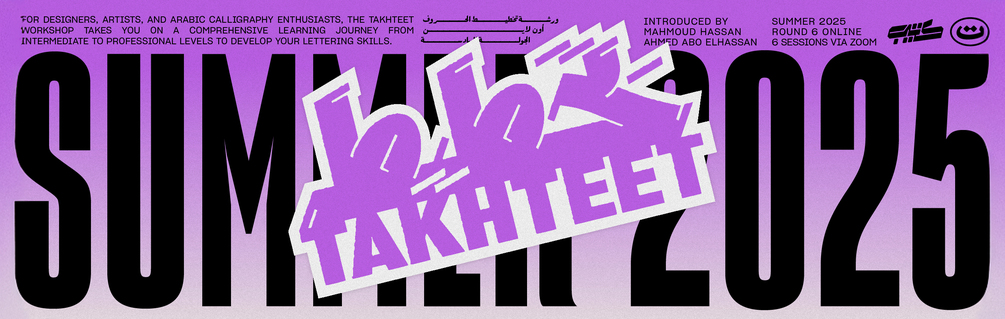
Takhteeet Arabic Lettering Online Workshop
نظرة عامة على الورشة:
ورشة "تخطيط الحروف" ورشة عمل عن بعد شاملة للمصممين والخطاطين لاحتراف تخطيط وتصميم الحروف العربية.
يقدمها أحمد أبوالحسن، مخطط حروف ومصمم هويات بصرية
ومحمود حسن، مصمم هويات بصرية ومخطط حروف ومدوّن في مجال التصميم.
* سيتعرف المشاركون على أساسيات الخط العربي ويتدربون على أنماط فنية مستوحاة من الخطوط الكلاسيكية والتصاميم الهندسية الحديثة.
* تغطي ورشة العمل العملية الكاملة لكتابة الكلمات بالخط، بدءًا من العثور على الإلهام وإجراء البحث إلى رسم المفاهيم الأولية، تنقيح التصاميم، ورقمنة العمل النهائي. من خلال التمارين العملية والإرشاد الشخصي من المدربين، سيطور المشاركون أساليبهم الخاصة في الخط ويكتسبون مهارات عملية في الطباعة وتكوين التخطيط.
* بحلول نهاية الورشة، سيكون لدى المشاركين أعمال خطية ومشروع نهائي يعكس رحلتهم الإبداعية والمهارات الجديدة التي اكتسبوها.
Workshop Overview:
Takhteeet Workshop is a comprehensive remote workshop for designers and calligraphers to master the art of Arabic lettering.
Presented by:
• Ahmed Abo El Hassan, lettering Artist and Branding Designer
• Mahmoud Hassan, branding designer, Lettering Artist, and Blogger about the Design industry
What the workshop includes:
• Participants will learn the fundamentals of Arabic calligraphy and practice artistic styles inspired by classical scripts and modern geometric designs.
• The workshop covers the complete process of lettering, from finding inspiration and conducting research to sketching initial concepts, refining designs, and digitizing the final work. Through hands-on exercises and personalized guidance from the instructors, participants will develop their own lettering styles and gain practical skills in lettering and composition.
• By the end of the workshop, participants will have completed lettering works and a final project that reflects their creative journey and the new skills they have acquired.